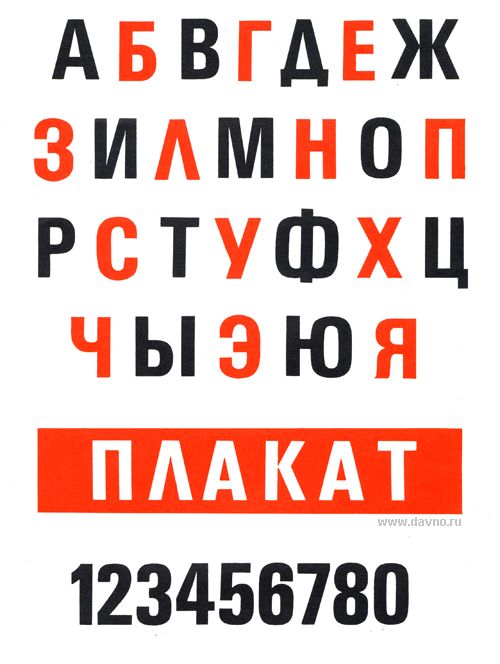
Proto Grotesk Regular
Характер у Proto Grotesk одновременно необычный и простой.
У него сложная родословная — здесь есть черты египетских и модернистских шрифтов, сочетаются округлые и острые формы, а в отдельных знаках появляются брусковые засечки.У него сложная родословная — здесь есть черты египетских и модернистских шрифтов, сочетаются округлые и острые формы, а в отдельных знаках появляются брусковые засечки.
Многофункциональные шрифты за последние сто лет утратили почти все странности и яркие особенности, которые придавали им характер. В такой эволюции есть определенный смысл, но ничто не мешает разрабатывать шрифты строгие и своеобразные одновременно. Proto Grotesk основан на немецком гротеске конца XIX века — того времени, когда ценилась яркость визуального языка.
У него сложная родословная — здесь есть черты египетских и модернистских шрифтов, сочетаются округлые и острые формы, а в отдельных знаках появляются брусковые засечки. Несмотря на все эти противоречия, силуэт шрифта крепкий и прямолинейный. Характер у Proto Grotesk одновременно необычный и простой.Многофункциональные шрифты за последние сто лет утратили почти все странности и яркие особенности, которые придавали им характер. В такой эволюции есть определенный смысл, но ничто не мешает разрабатывать шрифты строгие и своеобразные одновременно. Proto Grotesk основан на немецком гротеске конца XIX века — того времени, когда ценилась яркость визуального языка. У него сложная родословная — здесь есть черты египетских и модернистских шрифтов, сочетаются округлые и острые формы, а в отдельных знаках появляются брусковые засечки. Несмотря на все эти противоречия, силуэт шрифта крепкий и прямолинейный. Характер у Proto Grotesk одновременно необычный и простой.
Многофункциональные шрифты за последние сто лет утратили почти все странности и яркие особенности, которые придавали им характер.
В такой эволюции есть определенный смысл, но ничто не мешает разрабатывать шрифты строгие и своеобразные одновременно. Proto Grotesk основан на немецком гротеске конца XIX века — того времени, когда ценилась яркость визуального языка. У него сложная родословная — здесь есть черты египетских и модернистских шрифтов, сочетаются округлые и острые формы, а в отдельных знаках появляются брусковые засечки. Несмотря на все эти противоречия, силуэт шрифта крепкий и прямолинейный. Характер у Proto Grotesk одновременно необычный и простой.Многофункциональные шрифты за последние сто лет утратили почти все странности и яркие особенности, которые придавали им характер. В такой эволюции есть определенный смысл, но ничто не мешает разрабатывать шрифты строгие и своеобразные одновременно. Proto Grotesk основан на немецком гротеске конца XIX века — того времени, когда ценилась яркость визуального языка. У него сложная родословная — здесь есть черты египетских и модернистских шрифтов, сочетаются округлые и острые формы, а в отдельных знаках появляются брусковые засечки.
Несмотря на все эти противоречия, силуэт шрифта крепкий и прямолинейный. Характер у Proto Grotesk одновременно необычный и простой.
Что выражают шрифты
Орёт с плаката шрифт Rodchenko, по деловому вещает Times New Roman и кружит на бумаге свой танец Edwardian Script.
Шрифты придуманы не ради красного словца, а для того, чтобы яснее передавать смысл текста, это такая одежка, по которой встречают. Ну и, во-вторых, это просто красиво.
На первый взгляд кажется, что за всю историю письменности придумано так много шрифтов, что разобраться в них просто невозможно. На самом деле все гораздо проще и все эти бесконечные вариации окружностей и палочек легко умещаются в стройную и простую систему.
Все шрифты делятся на четыре большие группы, как времена года или стороны света:
- антиква с засечками
- гротеск без засечек
- рукописные, имитирующие человеческий почерк
- акцидентные для заголовков и плакатов.
Антиква
Стиль: академический, классический, традиционный, консервативный, элегантный.
Где найти: деловые газеты, научные статьи, книги, учебники, документация.
Если бы шрифты можно было бы сравнить с цивилизациями, антиква, несомненно, была бы представителем западной.
Эти шрифты формальны, строги и имеют самую длинную историю. У них традиции и манеры. Особенность антиквы, как уже говорилось, засечки — накрахмаленные воротнички и манжеты букв, элементы, которые делают шрифт устойчивее, основательнее, аккуратнее. Антикве хорошо удается передавать смысл деловых документов, научных справочников и статей, больших объемных текстов. Бизнесмен с газетой скорее всего пробегает глазами антикву, студент, сдающий сессию, имеет дело с засечками.
Антиква старого стиля
Скругление засечек в местах примыкания к основному штриху и наклонная ось овальных элементов, умеренная контрастность.
Примеры: Arno Pro, Bembo, Dante, Stempel Garamond , Granjon, Poliphilus, Sabon.
Переходная антиква
Разница между основными и соединительными линиями в переходной антикве более явная, чем в старом стиле, но менее четкая, чем в антикве нового стиля.
Примеры: Times New Roman, Baskerville, Caslon, Georgia и Bookman.
Антиква нового стиля
отличается более сильным контрастом между основными и соединительными линиями, строго вертикальными овалами, тонкими и длинными засечками.
Примеры: Didot и Bodoni.